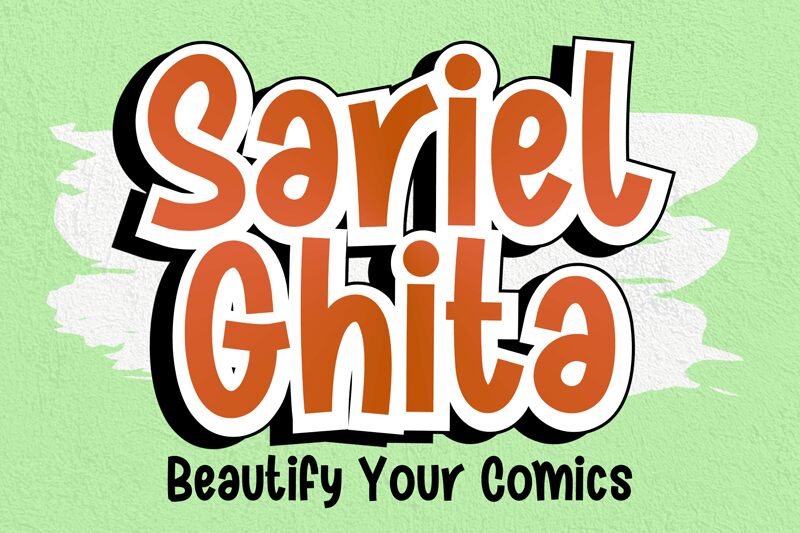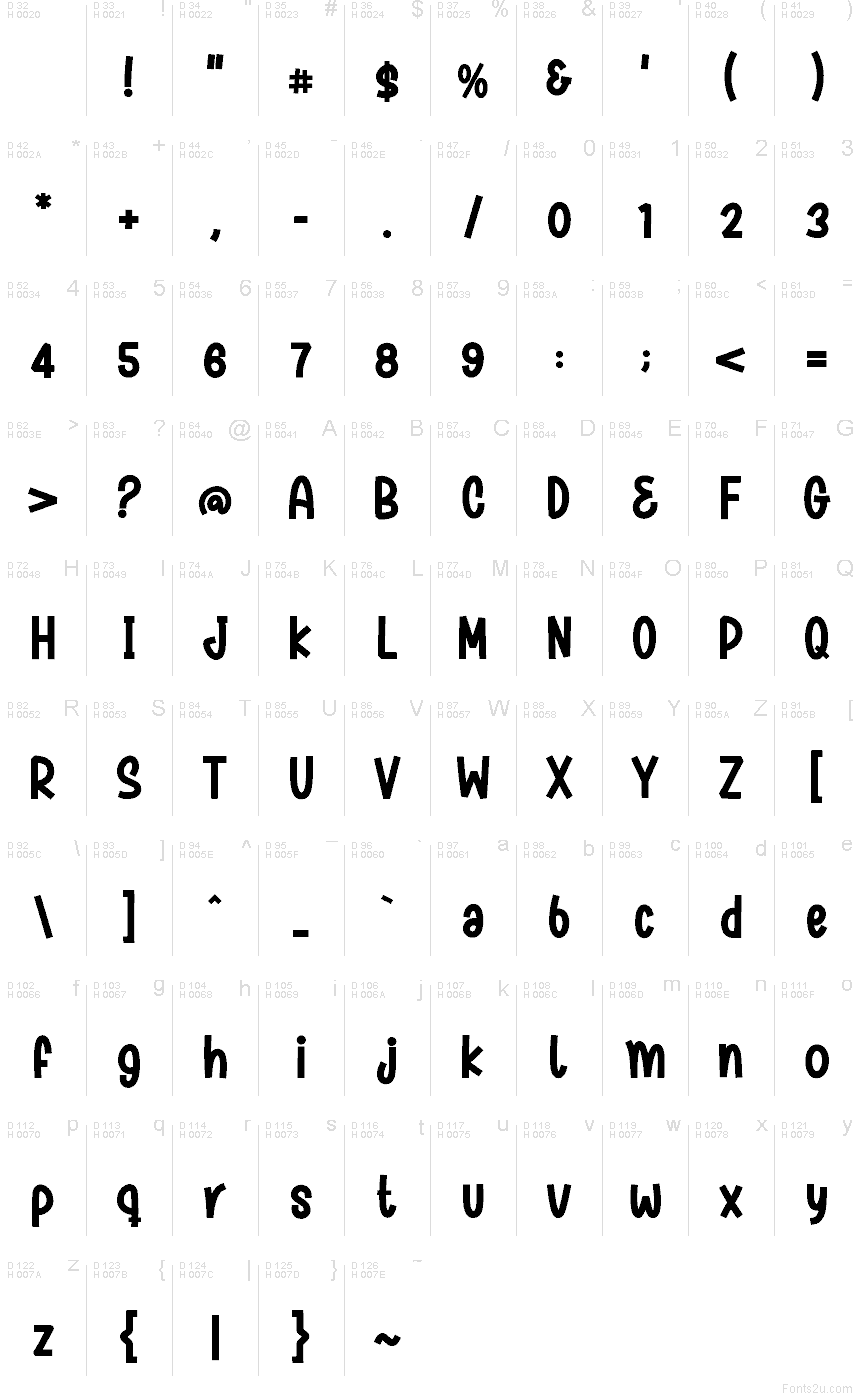
Sariel Ghita, stworzony przez Sariel Ghita z Mabhal Studio, to darmowy font typu display w stylu komiksowym, o wyrazistym, skocznym rytmie i lekko retro, popowym charakterze. Litery opierają się na miękkich, pełnych krzywiznach, które przełamują ostro zakończone łączenia i wycięcia w kształcie łezek – dzięki temu napis pozostaje żywy, a nie tylko „słodki”.
Ta mieszanka sprawia, że font świetnie sprawdza się w nagłówkach plakatów, brandingu dla dzieci, opakowaniach przekąsek, tytułach w stylu komiksowym czy zabawnych nagłówkach, gdzie darmowy font potrzebuje czegoś więcej niż zwykłe, „dmuchane” litery. Sprawdzi się też w krótkich logotypach czy wyróżnionych cytatach, ponieważ zaokrąglone formy są przyjazne w odbiorze, a jednocześnie ostre detale nadają krojowi psotnego pazura.